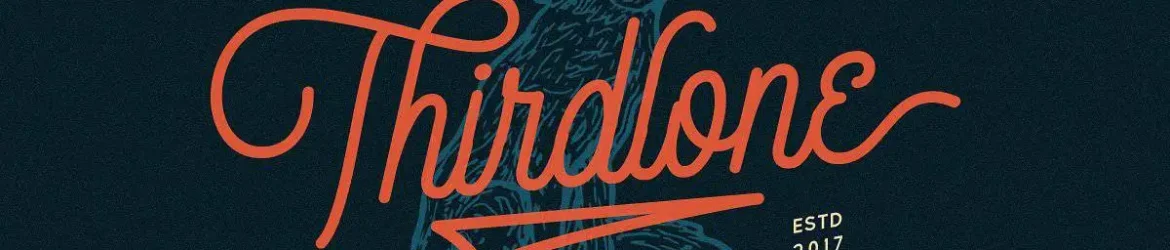
Descubra a Thirdlone Handmande Font, uma elegante tipografia script moderna e vintage, ideal para projetos variados. Desenvolvida pelo designer 24Design, esta font apresenta um estilo monoline com elementos de sans-serif, perfeitamente adaptável aos mais diversos usos gráficos. Com uma coleção imensa de objetos desenhados à mão em formato vetorial, você pode combinar estes elementos criativos com a Thirdlone Font para criar design exclusivos. A coleção inclui mais de 100 objetos em temas variados como aventura, natureza, animais, praia, mar, feriados e muito mais. Esta font é perfeita para uso em t-shirts, logomarca ou marca, assinatura, headlines, escrita de citações e muitos outros usos. Experimente a Thirdlone Font e adicione um toque único à sua identidade visual!